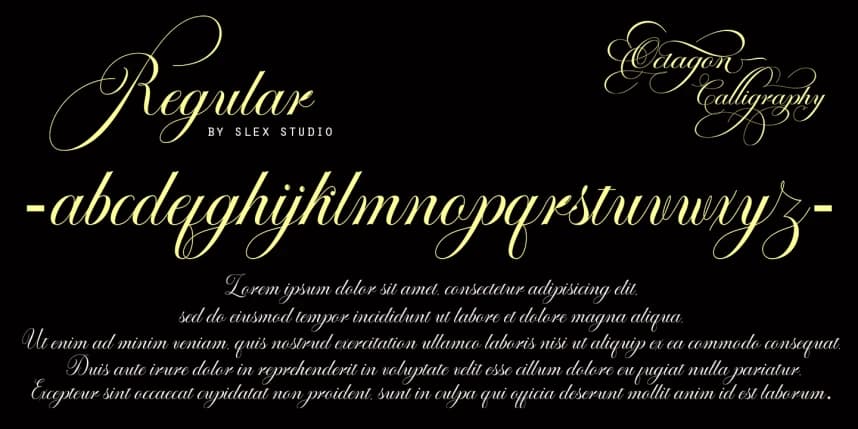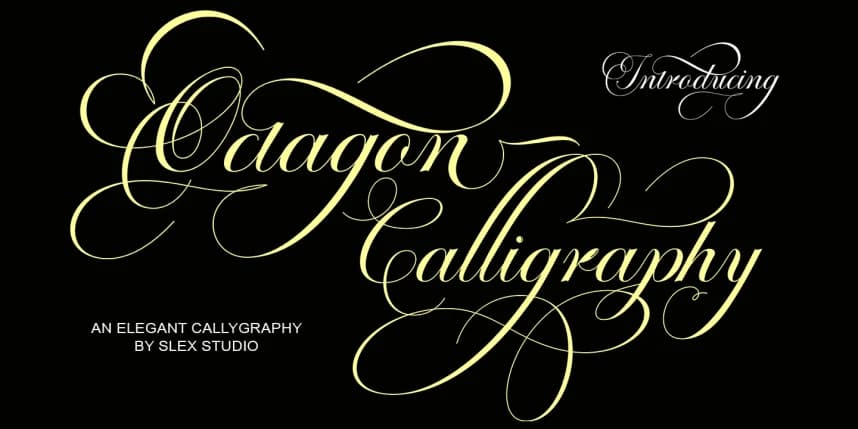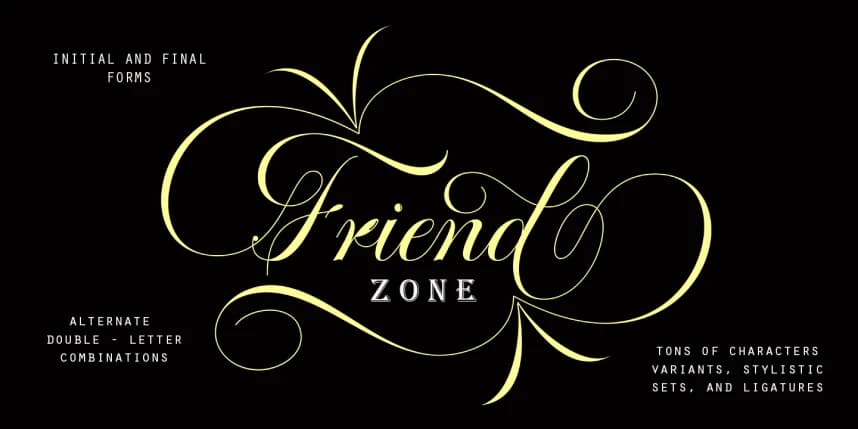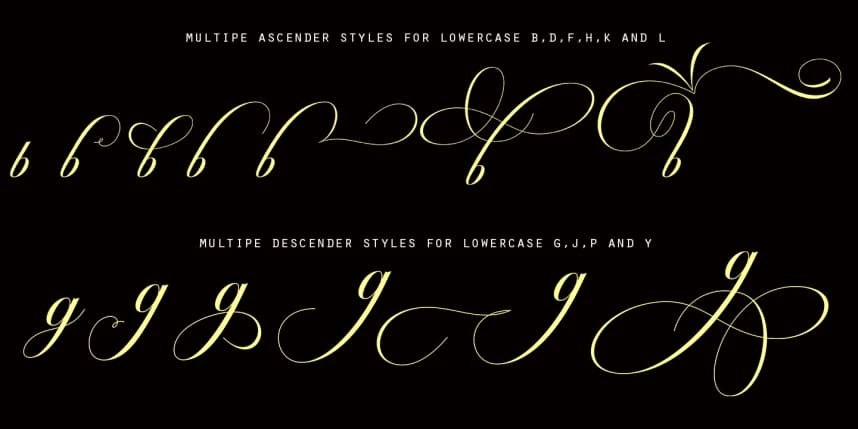
Octagon Calligraphy Font
Octagon Calligraphy Font, klasik bir stile sahip zarif bir kaligrafi fontudur ve kadınların el yazılarından ve eski el yazmalarından esinlenilmiştir. Birlikte uyum içinde çalışacak şekilde özenle tasarlandı ve bu da onu düğün medya içerikleri için çok uygun kılıyor.
Octagon Calligraphy Font, klasik bir stile ve zarafetin bir dokunuşuna sahip olan bir kaligrafi yazı tipidir; kadınların el yazılarından ve antik el yazmalarından esinlenmiştir. Birlikte uyum içinde çalışacak şekilde özenle tasarlanmıştır ve bu da onu düğün tanıtım materyalleri için çok uygun kılar.